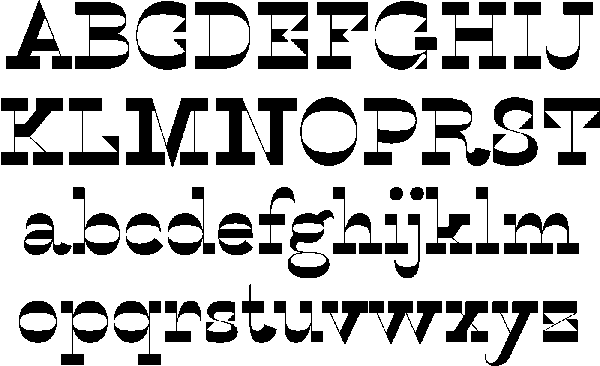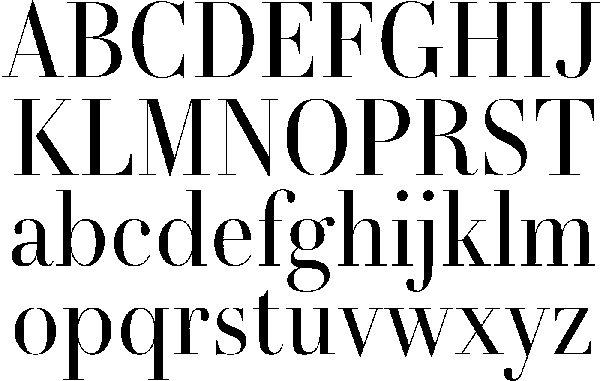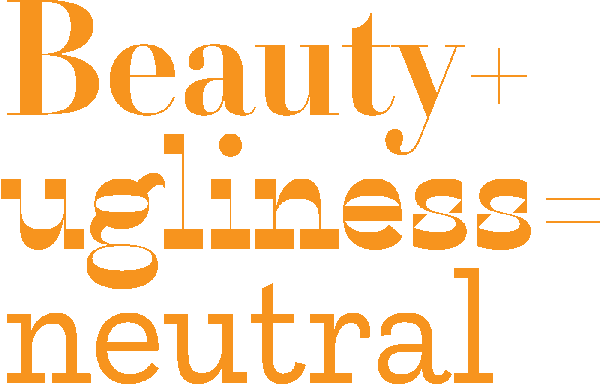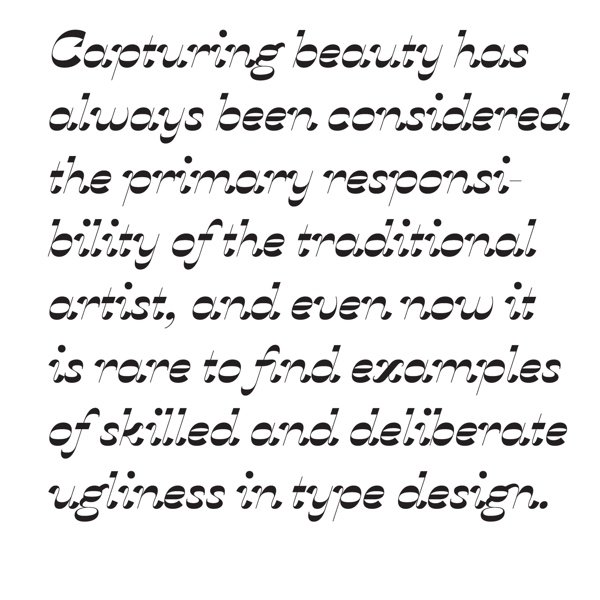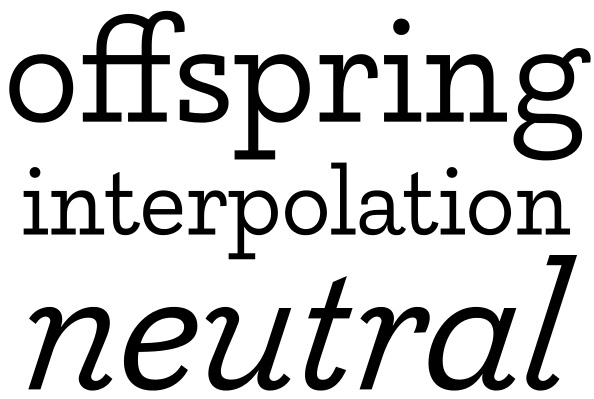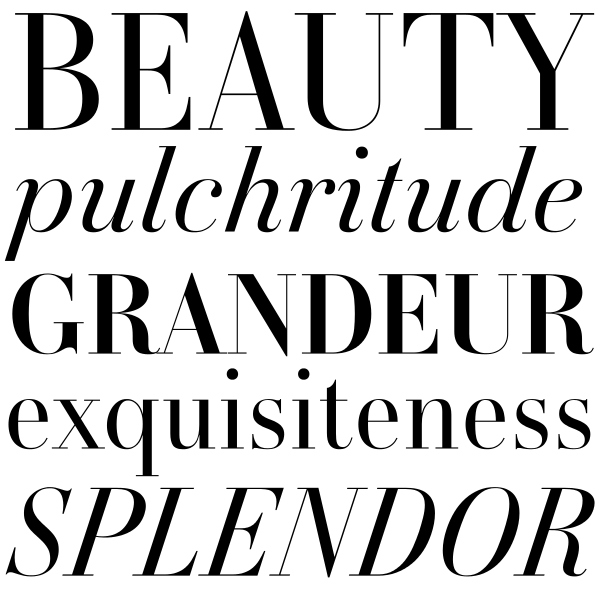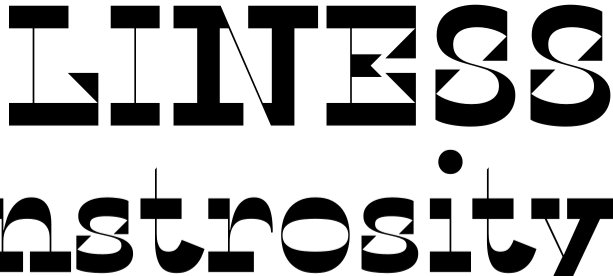
Karloff es la bella y la bestia de las tipografías. Diseñada por Peter Bi'lak, tipógrafo eslovaco afincado en los Países Bajos, Karloff hace converger de una manera peculiar la belleza y la fealdad en una tipografía que a la vez resulta proporcionada y monstruosa. La familia tipográfica está compuesta por tres pesos diferentes y sus respectivas versiones itálicas.
Karloff, Peter Bi'lak, 2012.
“Durante milenios la especie humana se ha esforzado por capturar los ideales de belleza. Los hemos buscado en las proporciones divinas, en la simetría y la armonía. Luchamos por definirlos, aunque los reconozcamos nada más verlos. La fealdad es diferente. Arremete contra nuestras expectativas. Viola todos los cánones y retuerce las convenciones. La fealdad nos repugna, aunque también incita nuestra atención voyeurísatica.“
Karloff es un experimento tipográfico que indaga en las relaciones intrínsecas entre la belleza y la fealdad. Ideada por el tipógrafo Peter Bi'lak, Karloff surge a partir de una conferencia de diseño tipográfico celebrada en Copenhague en 2010. El tema de la ponencia, la tipografía conceptual, hizo que el diseñador eslovaco se interrogue sobre la posibilidad de concebir especímenes que no persigan expresamente la legibilidad.
Izq: Didot, Pierre & Firmin Didot, 1784 – 1811. Dcha: Bodoni, Giambattista Bodoni, 1798. Fuente: Wikipedia.
Karloff comienza por estudiar las características que definen la belleza y la monstruosidad. Bi'lak escoge a Bodoni y Didot como las familias más representativas del canon tipográfico de belleza clásica: diseñadas respectivamente por los hermanos Didot y por Giambattista Bodoni a finales del siglo XVIII, las dos tipografías inauguraron el llamado periodo moderno. Didot y Bodoni extremaron los contrastes entre los trazos gruesos y finos, introdujeron remates largos y aplanados en las serifas, y confirieron un mayor peso a las mayúsculas. Los dos especímenes acabaron por encarnar el ideal de tipografía clásica gracias a su anatomía estilizada, su legibilidad y su fuerte presencia estética.
Italic, 1821. Fuente: I Love Typography.
En el extremo contrario, Bi'lak opta por Italian, una familia que persigue deliberadamente la deformidad. Nacida durante el siglo XIX con fines publicitarios, la fuente polariza la relación de trazos gruesos y finos en el cuerpo de las letras y exagera desmesuradamente sus remates. Italian viola sistemáticamente las convenciones tipográficas de la época con el objetivo de atraer la atención del lector.
Karloff Negative, Peter Bi'lak, 2012. Fuente: I Love Typography.
Karloff Positive, Peter Bi'lak, 2012. Fuente: I Love Typography.
Karloff es el resultado de la unión de los tres especímenes. Para Bi'lak, las diferencias entre la belleza de Didot y Bodoni y la monstruosidad de Italic son mucho menores frente a sus semejanzas. De esta manera, el proyecto se encarga de investigar los parametros comunes que detentan las tres familias, y arroja como resultado una tipografía compuesta por dos pesos diferentes, Negative y Positive.
Karloff Negative, Peter Bi'lak, 2012.
Karloff Positive, Peter Bi'lak, 2012.
Como sus propios nombres indican, Karloff Positive y Karloff Negative evocan en sus formas el clasicismo y el barroquismo, respectivamente. La diferencia entre ambas radica en el contraste entre sus trazos gruesos y delgados. Sin embargo, Karloff Negative y Karloff Positive se encuadran dentro de un mismo conjunto, ya que guardan una relación (diametralmente opuesta) en las proporciones y tamaño de sus astas y remates.
Las dos fuentes fueron creadas simultáneamente con la ayuda del también tipógrafo Pieter van Rosmalen. “Pudimos ajustarlas al mismo tiempo con el fin de obtener las mejores formas, más que subordinar una a la otra”, explica Bi'lak.
Karloff Neutral, Peter Bi'lak, 2012.
La familia Karloff se completa con Neutral, un peso que surge de la interpolación matemática de Negative y Positive. Su unión fue el resultado de un experimento casual que dió como resultado una fuente carente de grandes detalles y que imprevisiblemente evoca el carácter neutral de tipografías como Helvetica o Akzidenz Grotesk.
Karloff, Peter Bi'lak, 2012. Pesos Positive, Negative y Neutral. Fuente: I Love Typography.